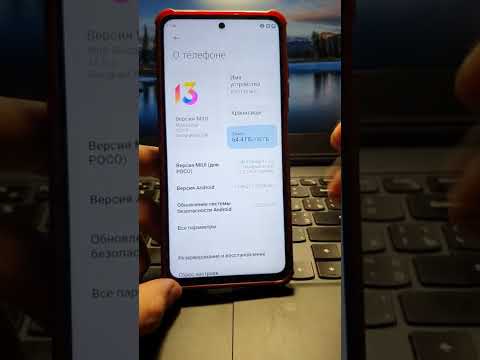
Идеальный шрифт для вашего андроид-устройства: советы по выбору и настройке
Хотите изменить шрифт на вашем андроид-устройстве, но не знаете, с чего начать? Узнайте, как выбрать лучший шрифт и сделать его уникальным и стильным с помощью наших советов.
Исследуйте разнообразие шрифтов: воспользуйтесь каталогами или приложениями, чтобы найти шрифт, который отражает вашу индивидуальность и подходит для разных ситуаций.
Учитывайте читабельность: выбирайте шрифты с хорошей читабельностью, чтобы не напрягать глаза и улучшить пользовательский опыт.
Настройте размер и стиль: экспериментируйте с размером и стилем шрифта, чтобы он хорошо выглядел на экране вашего устройства и соответствовал вашему вкусу.